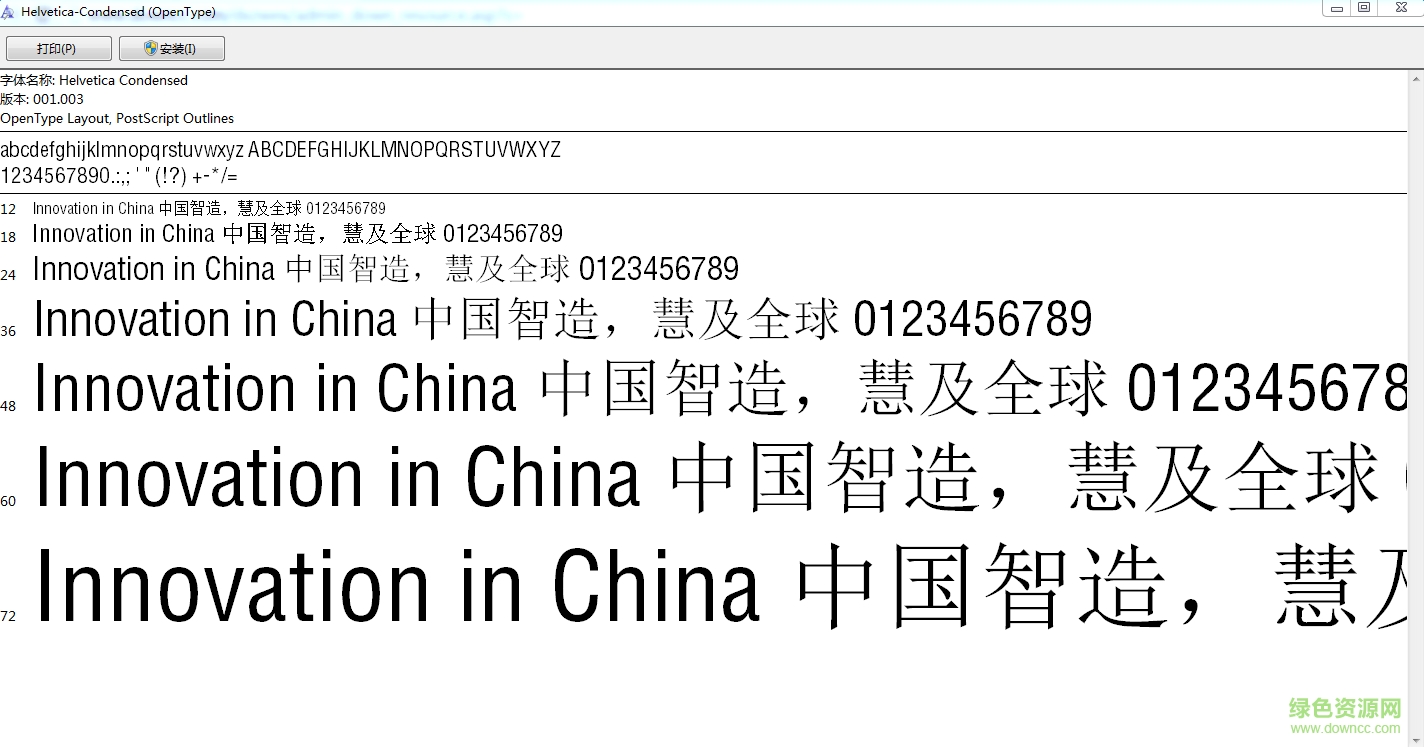
helvetica condensed英文字體
helvetica condensed字體是一款應(yīng)用廣泛的英文字體,字形簡(jiǎn)潔干凈,筆畫不尖,松緊有致,毫無多余點(diǎn)綴,整體效果精美又雅致,快來綠色資源網(wǎng)下載吧!
helvetica condensed字體整齊美觀又大方,大家可在廣告宣傳、ppt、產(chǎn)品包裝等領(lǐng)域使用這款字體!